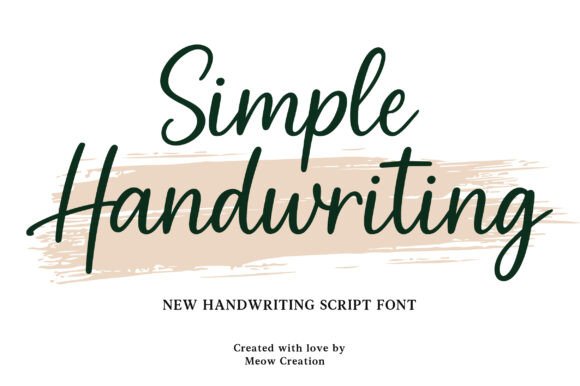
Simple Handwriting
Simple Handwriting – Revisão Completa e SEO‑Friendly
Se você procura uma fonte que combine elegância casual com legibilidade, a Simple Handwriting é a escolha certa. Criada para imitar a escrita à mão natural, ela traz um toque humano a projetos digitais sem sacrificar a clareza, tornando‑se ideal para branding, watermarks, legendas de redes sociais e assinaturas artísticas.
- Estilo contemporâneo e fluido: linhas suaves e conexões contínuas que simulam a escrita à mão relaxada.
- Peso médio e inclinação sutil: garante ótima legibilidade mesmo em tamanhos menores, diferentemente de scripts excessivamente decorativos.
- Versatilidade de uso: funciona perfeitamente em títulos, subtítulos e pequenos blocos de texto.
- Toque pessoal e acolhedor: transmite autenticidade, calor e proximidade ao leitor.
Aplicações Ideais
- Logotipos de marcas que buscam um visual humanizado e sofisticado.
- Marca‑d’água (watermark) discreta, mas distintiva, em fotos e ilustrações.
- Capítulos de e‑books ou newsletters que precisam de um toque pessoal.
- Legendas e descrições em Instagram, Pinterest e TikTok para destacar a voz da marca.
- Assinaturas digitais em obras de arte, convites e cartões personalizados.
A Simple Handwriting entrega o equilíbrio perfeito entre estilo artesanal e funcionalidade moderna. Seu design limpo, peso médio e leve inclinação a tornam uma das fontes script mais legíveis do mercado, capaz de transformar qualquer mensagem em algo quente, convidativo e memorável. Se o objetivo é criar uma identidade visual que fale diretamente ao coração do público, esta fonte deve estar no seu arsenal de design.